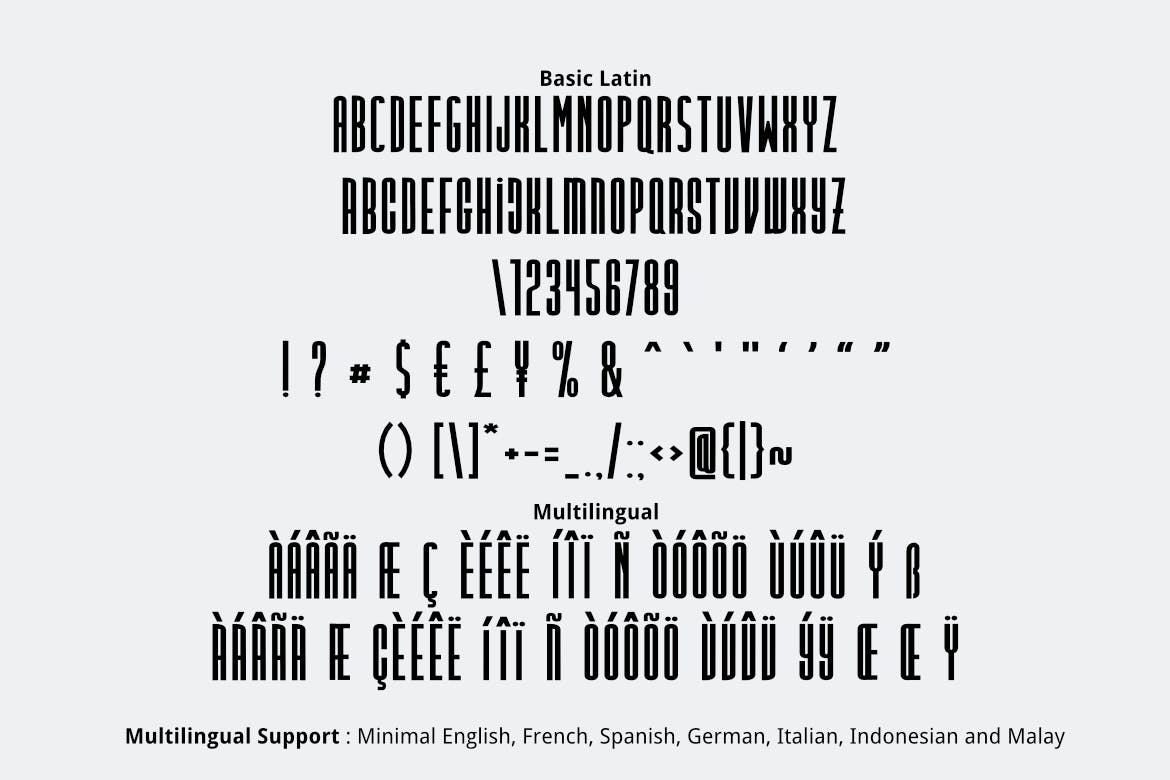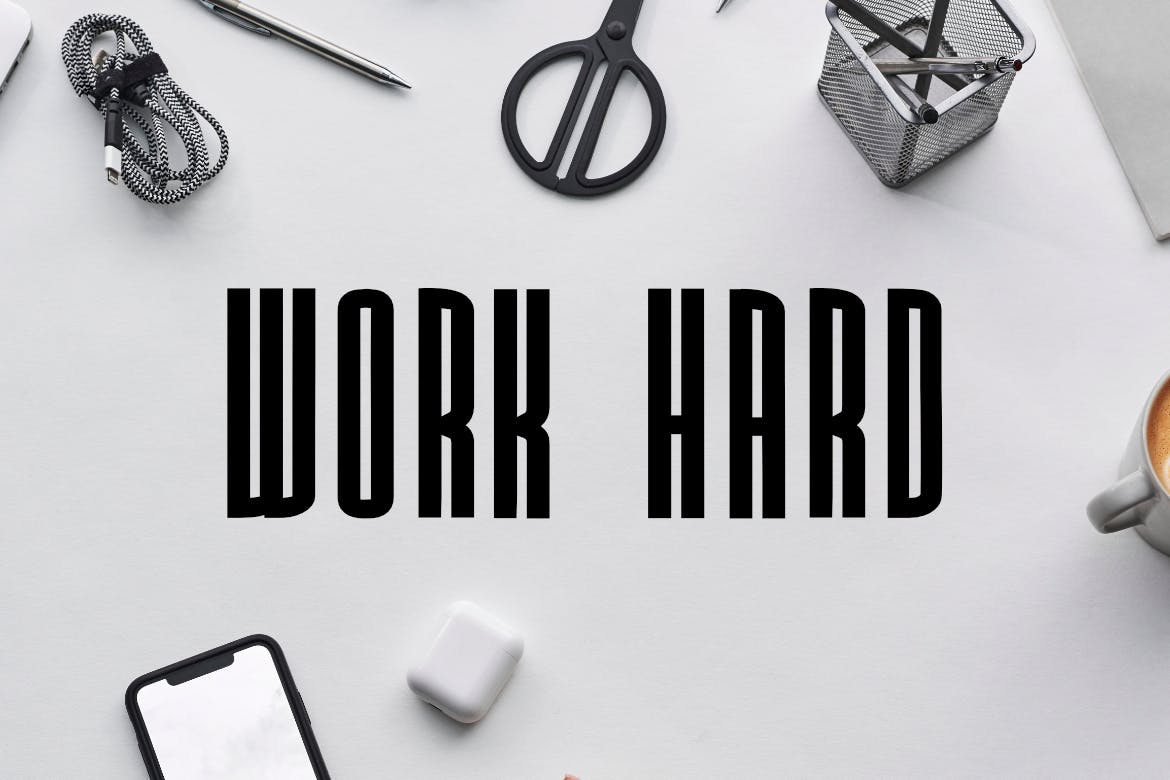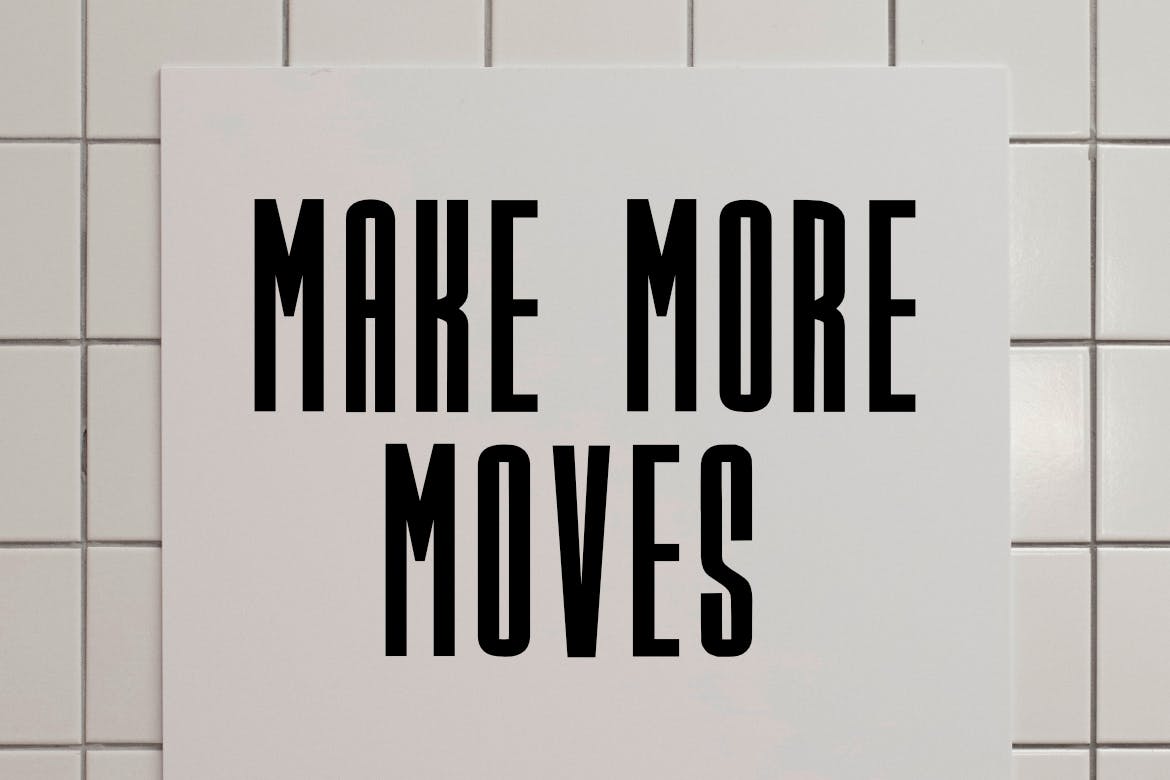
فونت Rathan
فونت Rathan یک فونت مدرن و آیندهنگر است که برای پروژههای متنوعی از جمله کتابهای کودک، نقل قولها، لوگوها، عناوین و تیترها بسیار مناسب میباشد.
این فونت از کاراکترهای لاتین پایه (کاراکترهای استاندارد انگلیسی، شمارهها و نمادها) و همچنین پشتیبانی چند زبانه (انگلیسی، فرانسوی، اسپانیایی، آلمانی، ایتالیایی، اندونزیایی و مالایی) بهرهمند است.